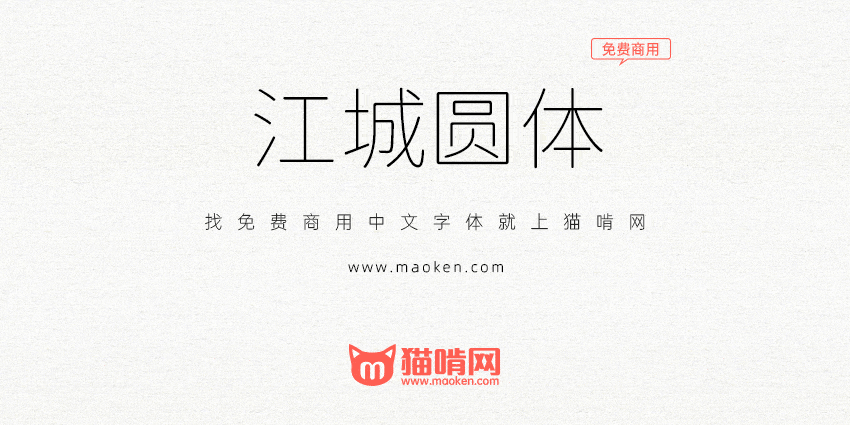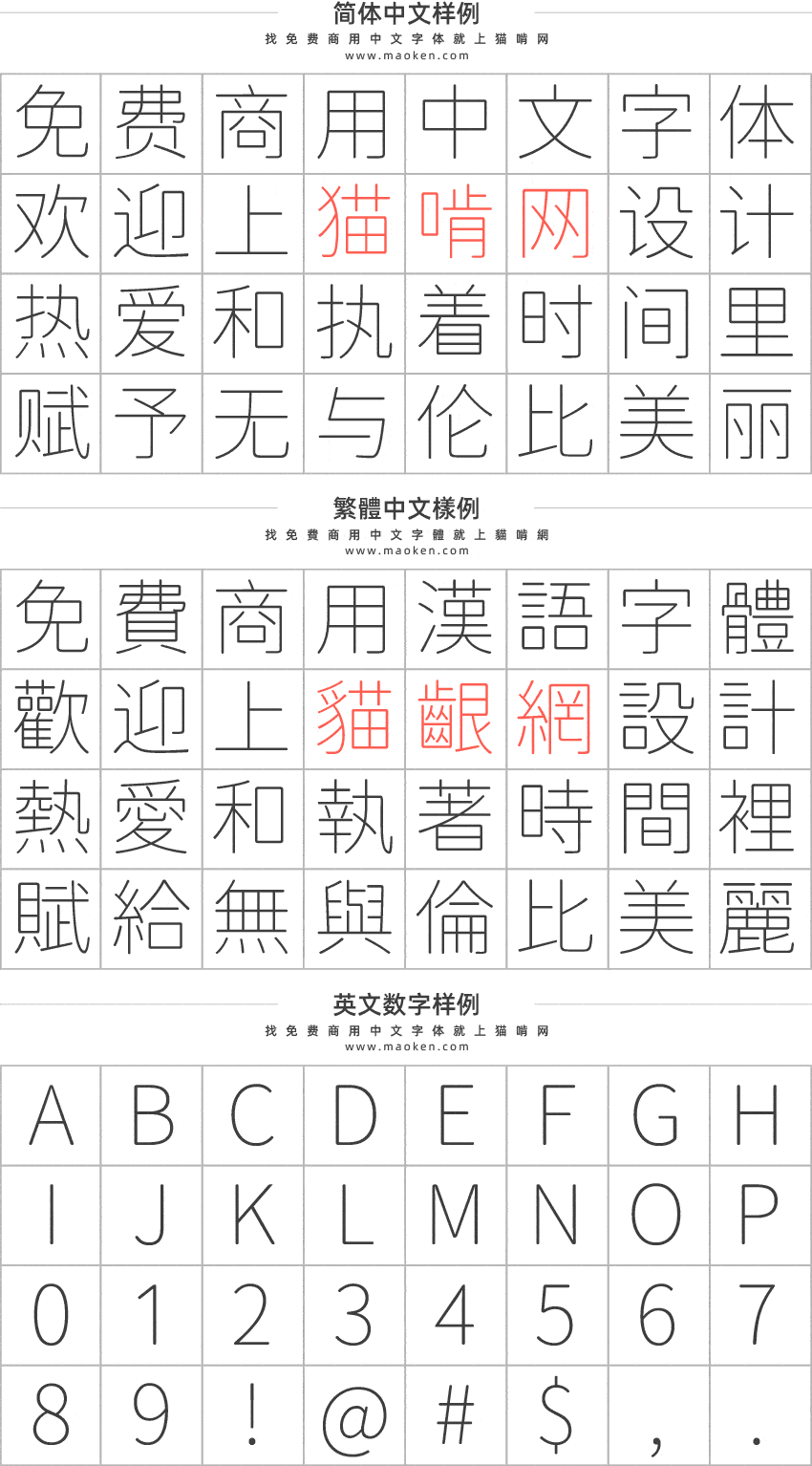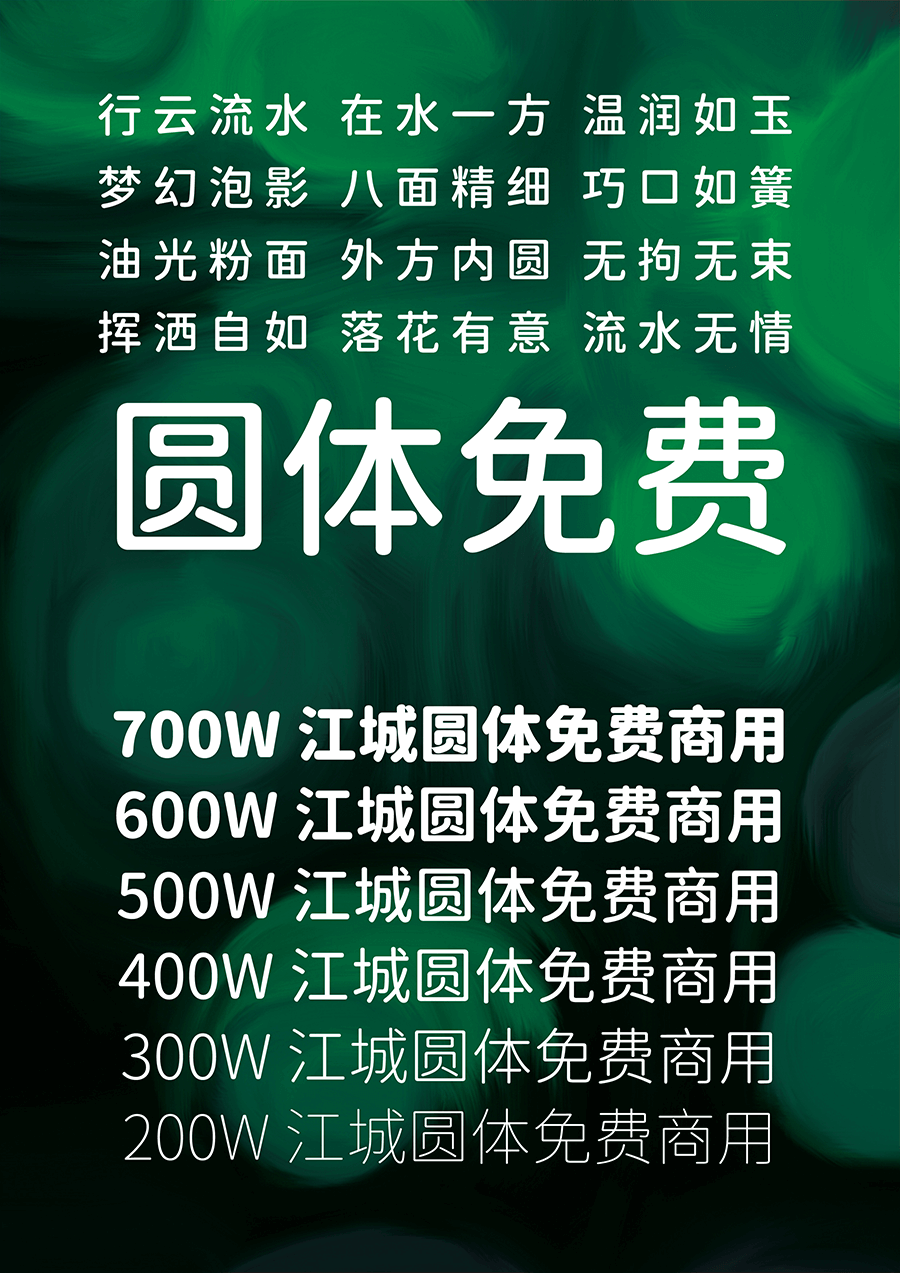
江城圆体:终于有一款比较适合国内设计师使用的圆体字形了
字体作者:刘鹏 (中国大陆) 字体字重:6个
猫啃网之前一直觉得没有一款比较适合的可以免费商用的圆体字形。在搜集免费商用中文字体的过程中,发觉大部分的文章都介绍使用“思源柔黑体”,后来我发表了一篇文章《源柔黑体:日本自家製フォント工房改造的思源字体》为“思源柔黑体”正名。因为这款字体应该叫“源柔黑体”而不应该叫“思源柔黑体”,具体原因大家可以看一下源柔黑体那篇文章。
猫啃网那时建议大家使用源泉圆体资源圆体替换掉网上一直流传的“思源柔黑体“,但是这两款字体对于中国大陆的设计师来说依然有点小瑕疵。源泉圆体因为是台湾设计师改造的字体,所以字形上会更贴近中国台湾的使用习惯。比如源泉圆体某些字的写法还是台版字形,而资源圆体则是思源黑体的直接变圆版,字形上保留着黑脚,看上去还是比较像黑体。
终于本站网友,一位被设计耽误的程序大神刘鹏,基于源泉圆体进行改造,把一些台湾习惯的字形进行简体化修正,发布了一款比较适合我们大陆设计师使用的字体”江城圆体“。这款字体基本源泉圆体改造,所以简体也是不缺少字的。并且有6个字重,十分贴心。猫啃网建议大陆的设计师们,可以把电脑上的源泉圆体删掉,替换成这款江城圆体吧!!江城圆体改过的字可以点击这里查看。
• 修改 僔噂墫嶟撙樽竴罇蹲鐏鱒
• 优化了部分字形
• 修改了约439个字X5个字重
• 西文字母及数字选用Baloo2
• 删掉了200W字重,全新为5个字重
• 修改了网友反馈的与常规写法有异的字
• 修改了包含“半”“肖”“力”“亡”“亥”“幺”“免”部件构形的异体字共计325个字
• 修改了约115个与常规写法有异的字体(6个字重)改过的字可以点击这里查看。
• 拔掉了700W字重下带“口”旁的字脚约49个字 改过的字可以点击这里查看。
• 修改了约135个与常规写法有异的字体(6个字重)改过的字可以点击这里查看。
• 拔掉了700W字重下啃、和、时等字脚。
• 江城圆体更新2.0版本,这个版本修改了约50个与常规写法有异的字体,改过的字可以点击这里查看。
• 江城圆体更新1.5版本,这个版本继续对部分字进行修改,改过的字可以点击这里查看。
• 江城圆体正式发布。江城圆体改过的字可以点击这里查看。
太棒了,圆体资源太少了
大佬你好,非常喜欢江城圆体,也使用了很久,感谢您的付出。请问近几个月是字体有过更新修改吗?“才”字的字形有一些变化,以前是正常的简体才,很漂亮。上个月使用时发现“才”字写法变了,非常像个提手旁,不像单独汉字了,使用起来也容易造成错别字误会,望看到
“网”不是国标字形,写法有异……
感谢作者,发现了与常规写法有异的字:蝉
大神你好! 字体竖排文字 行距过大 全角逗号没有 只有半角
行高可以修正一下吗?sketch里面用,打字出来 字不是在行高里居中的,很难受。。。 谢谢大佬们!
• 近期会更新,有修正行高问题
很不错的字体!希望能延续下去作者的风格哦,圆体太少了。超喜欢圆体哦
谢谢大佬!字体非常好~最新版本 3.6 还是有些字形问题,目前遇到的一些:
1、篇骗偏编遍扁……
2、深探……
3、俊酸……
4、孚俘浮捋……
5、沙纱莎砂痧……
6、旅……
另外,标点符号中的部分标点比如句号“。”顿号“、”等好像都不够宽?叹号“!”逗号“,”等是正常的。
• 哦,字形问题又发现一个:
7、将蒋……
liahbhobhuaki5年前 (2021-11-15)回复
11. #40
你好,江城圆体非常漂亮,感谢您的付出,淘宝首页,拼夕夕首页字体下沉
man5年前 (2021-11-04)回复
• 谢谢,此字体主要用于电脑办公设计使用,手机字体使用暂不会处理
刘鹏5年前 (2021-11-05)回复
12. #39
还是喜欢以前的数字字母,有3.1版本下载么
火喵5年前 (2021-10-13)回复
13. #38
芒字下面的亡没超出去
JANVA5年前 (2021-09-02)回复
14. #37
AI 2019 先选字体 再选字体样式 字重全部显示为Regular 直接从字体下面选字重 就正常
梅花55年前 (2021-08-11)回复
15. #36
在Indesign中无法正常使用,只显示粗体字,选其他字号都是粗体。
大哭狗5年前 (2021-07-23)回复
16. #35
我用这个字体做ass格式的字幕,出现了很诡异的事情:
以“♥”为基础符号,分别转了0°、90°、180°、270°,构建出四叶草的四片小叶
然后自然就是调整坐标的位置使之对称
对称的两片小叶居然不在同一水平线或纵轴线上
而我用微软雅黑就不会有这个问题
fuyouquan5年前 (2021-06-26)回复
17. #34
为什么PS300字重变成独立字重了,没有和400/500/等收纳在一起
慕白5年前 (2021-05-05)回复
• 我用PS CC 2019测试没有问题,你可以把字体删除干净后,再重新安装
刘鹏5年前 (2021-05-06)回复
18. #33
这是最新版的吗?
白鸟5年前 (2021-04-29)回复
• 你好,是的~
猫啃网5年前 (2021-04-29)回复
19. #32
江城圆体更新V3.4版本了,已发站长QQ一份
1、修复了字体名称显示拼音问题
2、修改了约439个字X5个字重
刘鹏5年前 (2021-04-28)回复
• 你好,最新版打两个ff以上会出问题。
Sam5年前 (2021-06-03)回复
• 字体下沉,望修复
逍遥医道5年前 (2021-10-10)回复
20. #31
请问江城圆体有繁体字体包么?
玥玥小公举6年前 (2021-04-19)回复
• 字体本身就包含繁体,要输入繁体字才会显示繁体
刘鹏6年前 (2021-04-20)回复
• 江城圆体是 GBK 字集的,本身包含繁体字。
lxgw6年前 (2021-04-20)回复
21. #30
感谢作者,刘大人,谢谢
Sam6年前 (2021-04-08)回复
22. #29
为什么不修复行高呢?在PS里使用,行高大了,来个修复行高版 这样就是很好用的字体啦
喵哥6年前 (2021-03-28)回复
• Ps里的行高问题,我暂时不知如何解决,同时也请会的大神指导指导。
刘鹏6年前 (2021-03-28)回复
23. #28
字体名称显示好像变成拼音了,3.1时双击预览是江城圆体,3.3是jiangchengyuanti
HeadlessKnight6年前 (2021-02-26)回复
• 我测试过,安装后是中文名。
刘鹏6年前 (2021-02-26)回复
• 虽然文件显示英文,但不影响使用,我研究下,尽量下个版本修复。
刘鹏6年前 (2021-02-26)回复
• 突出的突不是大陆写法
困困6年前 (2021-02-27)回复
• 感谢反馈问题,下个版本修复
刘鹏6年前 (2021-02-27)回复
24. #27
中文样例和数字英文样例都以及字重都有修改,辛苦站长重新更新了
刘鹏6年前 (2021-02-21)回复
• 为什么不修复行高呢?在PS里使用,行高大了,来个修复行高版
喵哥6年前 (2021-03-28)回复
25. #26
https://weibo.com/1960937691/K2XPhySHR?ref=home&type=comment#_rnd1613893674032
江城圆体更新3.3版本了,已发站长QQ一份
1、修复了竖排文字会有叠加bug;
2、西文字母及数字选用Baloo2;
3、删掉了200W字重,全新为5个字重;
4、修改了网友反馈的与常规写法有异的字。
刘鹏6年前 (2021-02-21)回复
• 你好,请问有3.1版本下载么,我不喜欢新版的数字字母,找不到下载地址
火喵5年前 (2021-10-13)回复
• 你加下我QQ179383817也可以,我还有3.1版
猫啃网5年前 (2021-10-13)回复
26. #25
作者您好,“灵”字上面的“彐”中间一横太长了,穿过了竖。望修复!?
特没谱6年前 (2021-02-20)回复
• 厉害,为什么你能发一朵小花出来的?
猫啃网6年前 (2021-02-20)回复
• 就是emoji而已?
特没谱6年前 (2021-02-20)回复
• Emoji表情??❤️
刘鹏6年前 (2021-02-20)回复
• 收到,我加紧更新修复。?
刘鹏6年前 (2021-02-20)回复
• 其实是其他区域常用字形(彐一般作成伸出的爪子,伸出的横拟似手腕)。
夜煞之乐6年前 (2021-02-21)回复
27. #24
直排文字会有叠加bug
1116年前 (2021-01-27)回复
• 更新3.1版本出现的问题,3.0版本是没问题的,抽空我重新修复下
刘鹏6年前 (2021-01-27)回复
28. #23
Baloo2是开源的吧?我想把这字体替换到江城圆体里面
刘鹏6年前 (2020-12-24)回复
• Baloo2可以用来修改~
猫啃网6年前 (2020-12-24)回复
29. #22
“口”字没有拔脚
肥羊菌_6年前 (2020-10-25)回复
• 700W字重下有不少“口”带脚,其他字重正常,下次更新先修复常用字
刘鹏6年前 (2020-10-25)回复
30. #21
江城圆体3.1-字形异常:简体:比(左下角折弯),今(人字应出头)
Kuiba6年前 (2020-10-15)回复
• “今”的人字头不出头不是圆润吗?更符合圆体特征。
刘鹏6年前 (2020-10-25)回复
• 确实,但是思源黑体本身视这个为区域差异。
夜煞之乐6年前 (2021-02-21)回复
31. #20
江城圆体更新3.1版本:
1、修改了网友反馈的与常规写法有异的字;
2、修改了包含“半”“肖”“力”“亡”“亥”“幺”“免”部件构形的异体字;
共计325个字。
https://weibo.com/1960937691/Jp2JL1voy?ref=home&type=comment#_rnd1602597632319
刘鹏6年前 (2020-10-13)回复
32. #19
腿 有问题
教父6年前 (2020-10-11)回复
33. #18
牛批,老大有考虑加入韩语吗?
卤肉惠方卷6年前 (2020-09-07)回复
34. #17
3.0异体:网、般、突、准、怎、以、羞、么
肥羊菌_6年前 (2020-08-27)回复
35. #16
看这情况还是没完美吖,目前还不能是推荐字体吧。还是慢慢等完美吧
困困6年前 (2020-08-05)回复
• 该字体以我一人之力恐怕难有完美的一天,只能尽量把常用字修复。个人能力时间有限,完全是兴趣支撑,否则早已放弃。该字日常设计用于海报标题等是绰绰有余,不建议用于文章正文,正文还是乖乖用思源黑体哦。
刘鹏6年前 (2020-08-20)回复
• 做字体不易,非常感谢,喜欢这款,名字也好听
程序员6年前 (2020-08-28)回复
36. #15
带⺶的字写法好像都有错
肥羊菌_6年前 (2020-07-26)回复
• 最新更新V3.0版本,已更新你反馈的字。带⺶的字我只找到“着差溠羌”已更新,暂时我没想到什么字。
刘鹏6年前 (2020-08-20)回复
• 推荐你下载个汉字博字,找带偏旁的字体非常容易
猫啃网6年前 (2020-08-20)回复
37. #14
着、突、溢、敢、繁、会、云、去、言、护
这几个字的写法有异
肥羊菌_6年前 (2020-07-26)回复
38. #13
发现一个问题,带“子”的文字,圆体和黑体一样,比如字、李……,“了”没有弯
achair6年前 (2020-07-20)回复
• 我查看了你说的“子字李了”等字没有问题
刘鹏6年前 (2020-08-20)回复
39. #12
2.5版本异体:抱花言苹翟窄寨瞧壳鞘峭着股护斛槲弯湾瞧歉黔薪衅耀濯擢灼啄琢涿考残汛酸尘准蹭推豪蒋低(“低”字下面一点太细了,可以对比一下“底”)
喵星人6年前 (2020-07-15)回复
40. #11
2.0版本与常规写法有异的字体:异、确、底、哥、歌、喝、信、瘟、船、勤、骨、塌、榻、猜、践、化、椎、之、新、省、条、亲、圈、考、徘、家、嫁、没、幼、稚、深、空、嗟、妙、秒、抄、吵、炒、嘲、紫、外、奏、辣、唯、惟、微、孩、卿、蜻、疫、象、商、畜、泡、萢、砲、脬、豹、翅、罔、惘、魍、隔、
喵星人6年前 (2020-06-15)回复
• 舟、亮、灰、朵、躲、警、判、梅、没、海、毒、舟、俞、渝、愈、涉、隧、
喵星人6年前 (2020-06-15)回复
• 发邮件告诉作者,好像他很忙吧没看到
困困6年前 (2020-06-25)回复
• 你反馈的在V2.5版本经更新了哦
刘鹏6年前 (2020-07-15)回复
41. #10
路径的“径” 右边看起来像“圣”
helen6年前 (2020-06-12)回复
• 已记录,下次更新修复
刘鹏6年前 (2020-06-12)回复
42. #9
系、素、两字的小字下面少了一个小勾
白易居士6年前 (2020-06-11)回复
• 下次更新修复
刘鹏6年前 (2020-06-12)回复
43. #8
用简体输入【浅】【零】【雅】【滔】,字体显示与常规简体有出入
sa3m6年前 (2020-06-11)回复
• 下次修复
刘鹏6年前 (2020-06-11)回复
44. #7
貓啃網!max32002的台灣粉圓 TaiwanPearl發佈了!
究極亞米緹Official6年前 (2020-06-10)回复
• 感谢您提供信息~
猫啃网6年前 (2020-06-10)回复
45. #6
这款字体的“复”字有点奇怪,比其它字瘦了一半。
喵星人6年前 (2020-06-09)回复
• 还有“类”字下面多了一点,“大”成了“犬”;“将”、“曾”也不是大陆写法。
喵星人6年前 (2020-06-09)回复
• 称、港、煽、角、触、解
喵星人6年前 (2020-06-09)回复
• 收到,有问题可以修复
刘鹏6年前 (2020-06-09)回复
• 在吗,蒋 字写法有问题 ,谢谢
教父6年前 (2020-10-01)回复